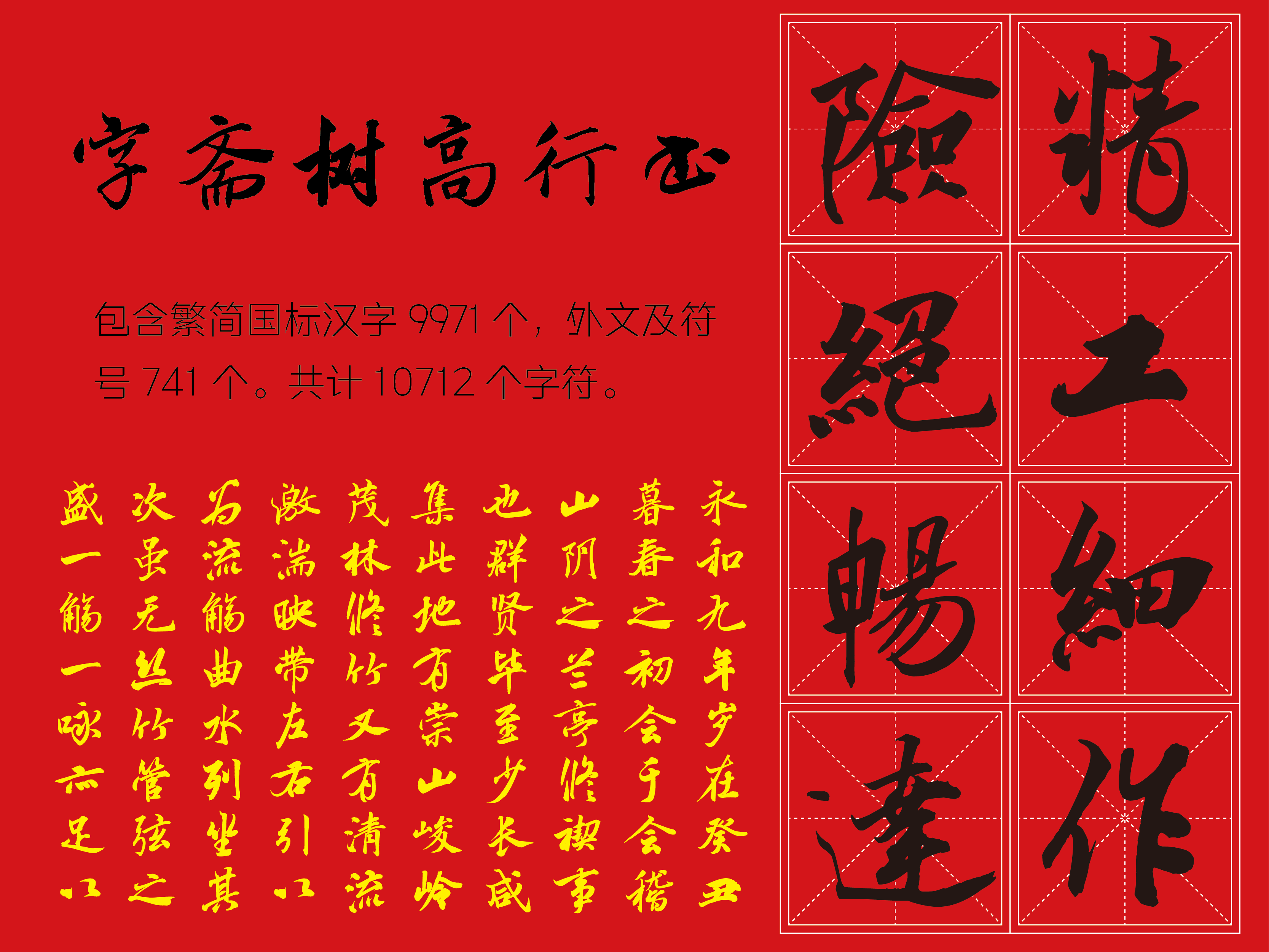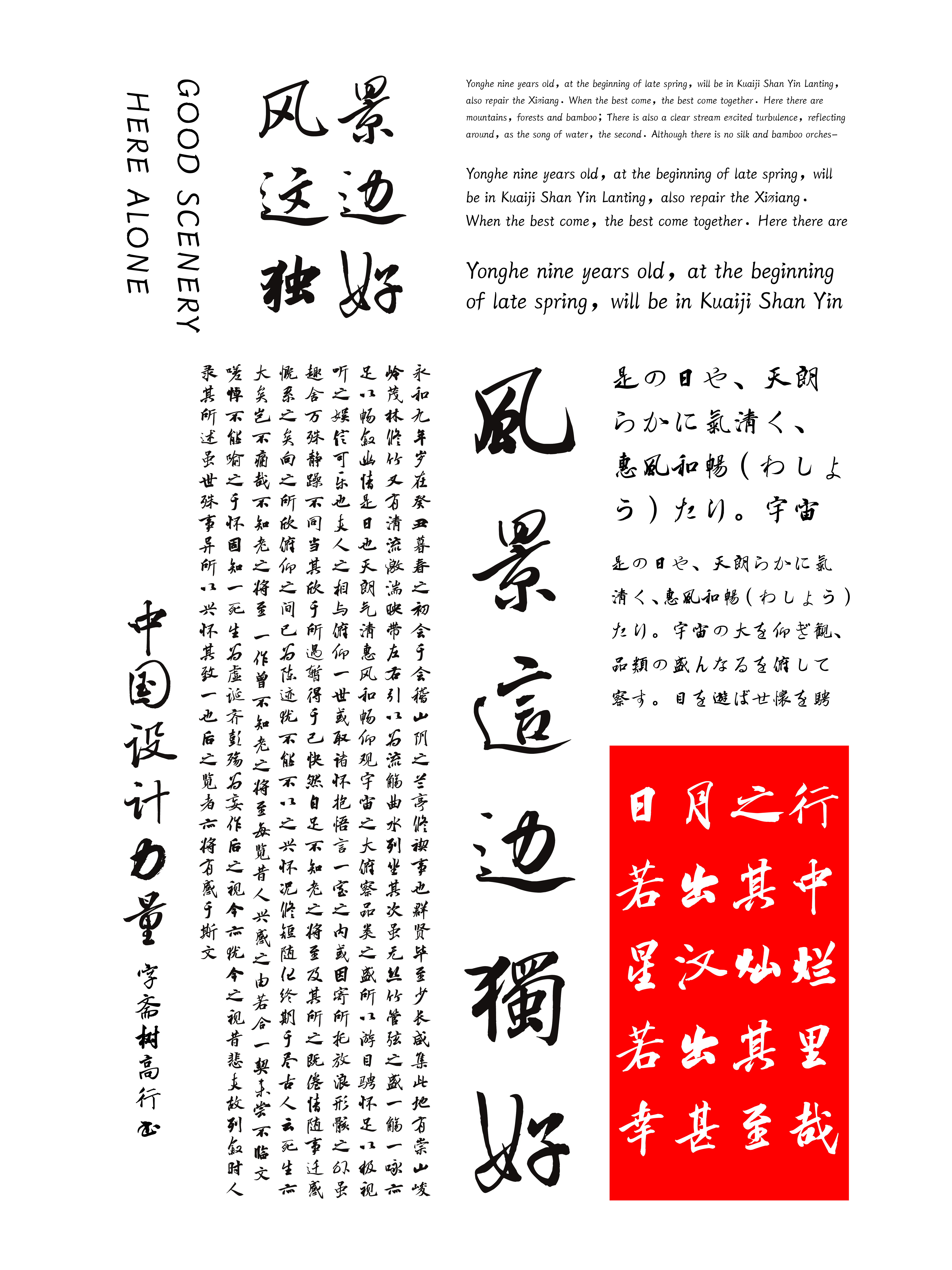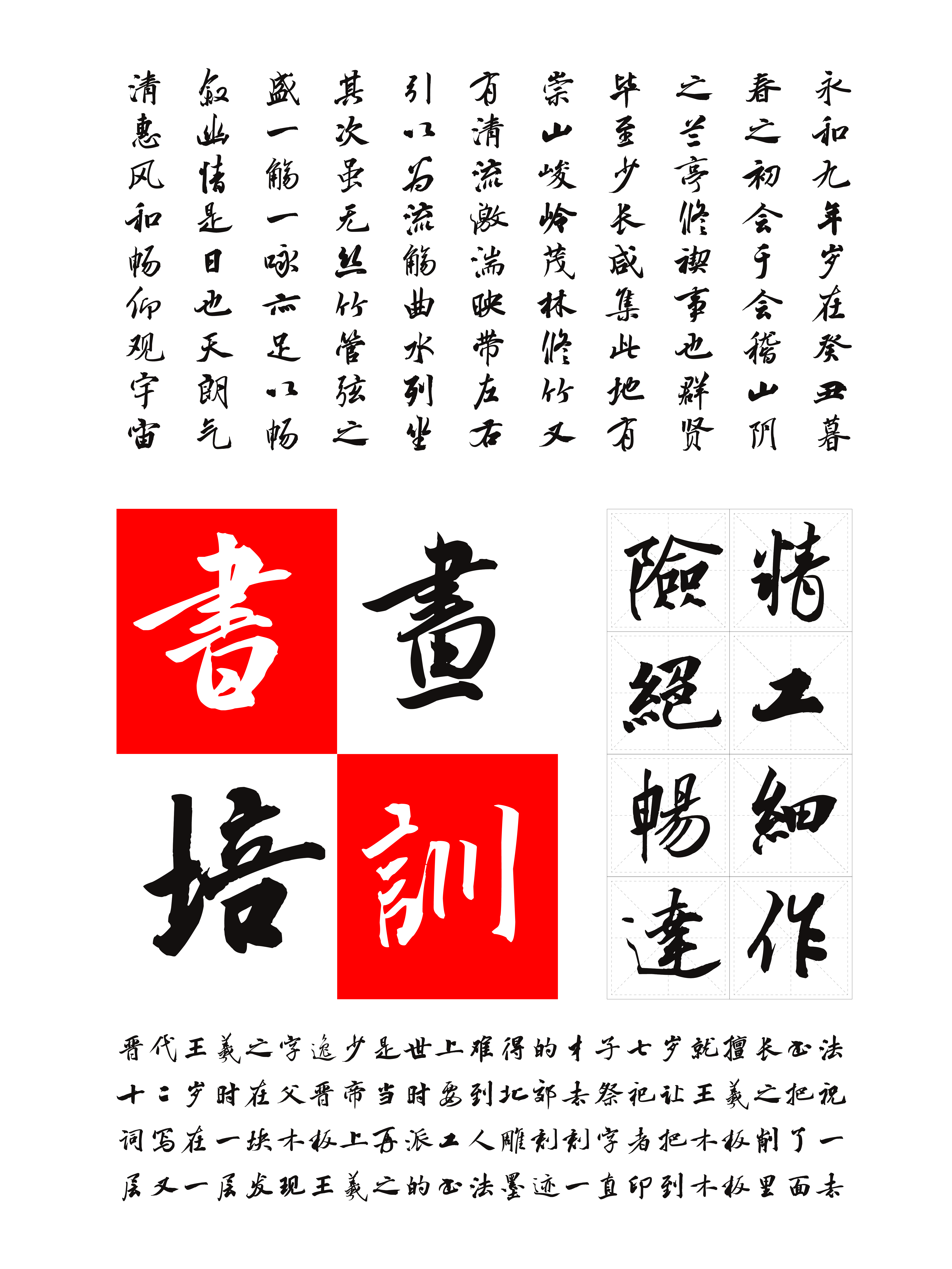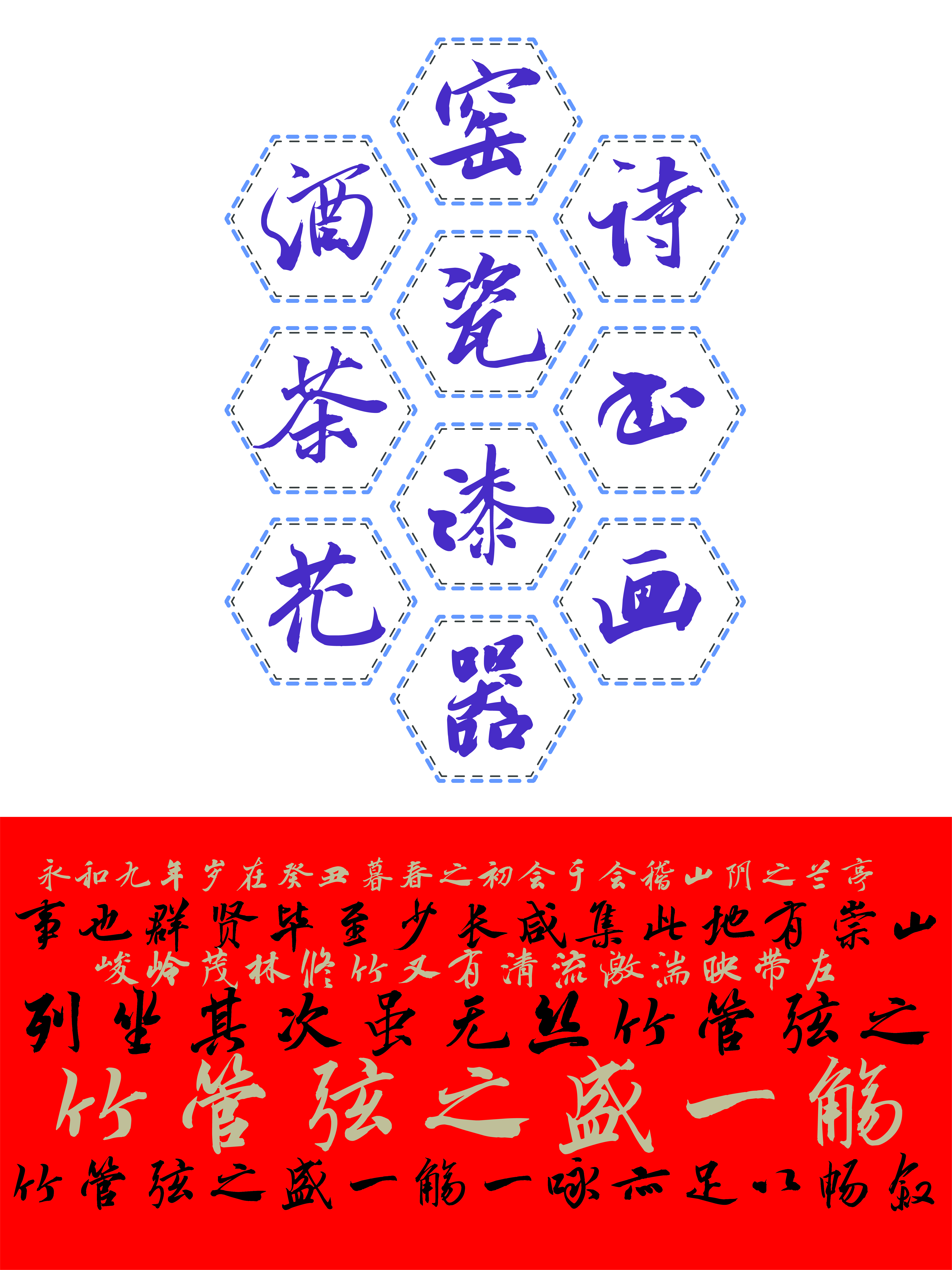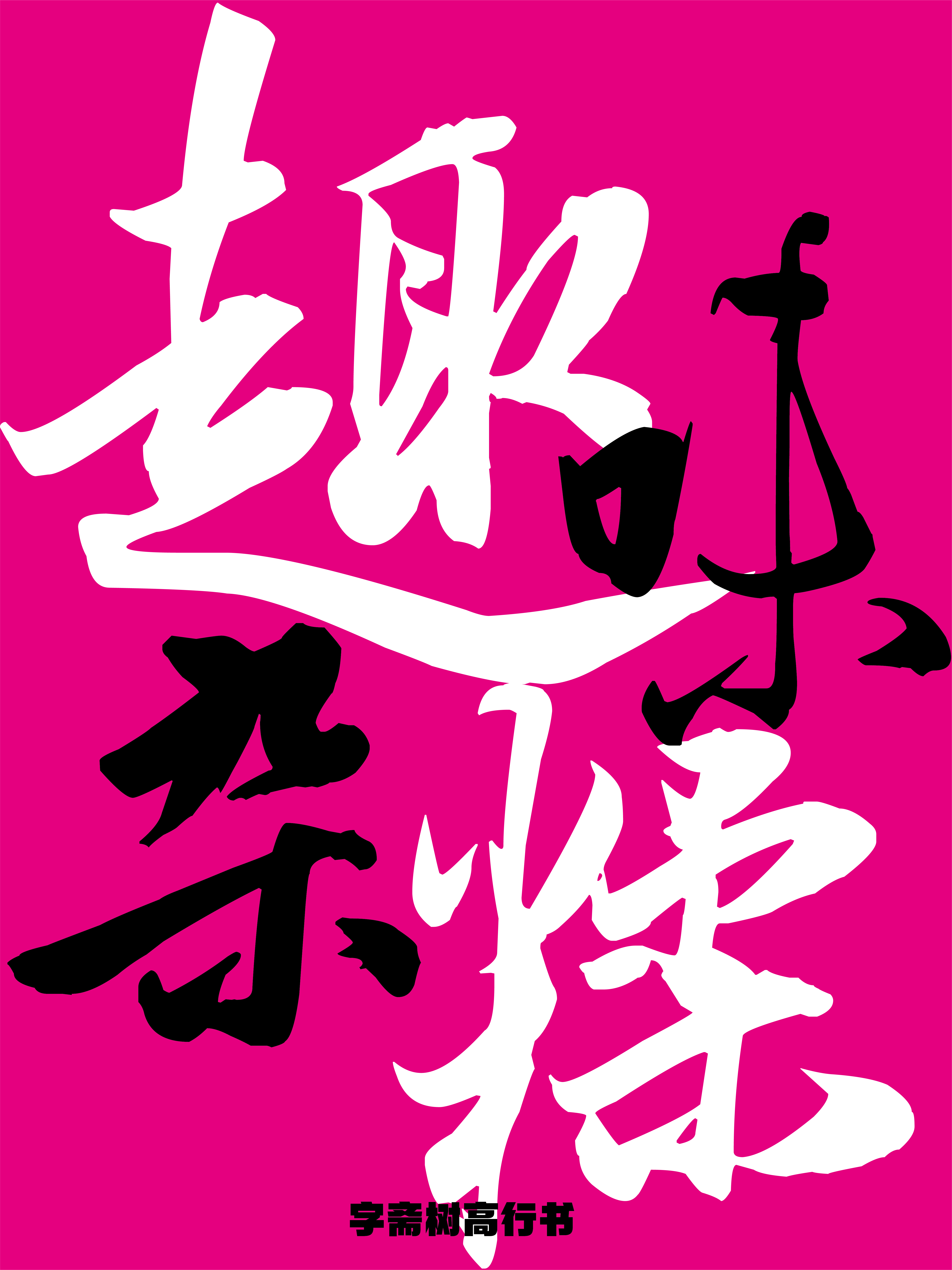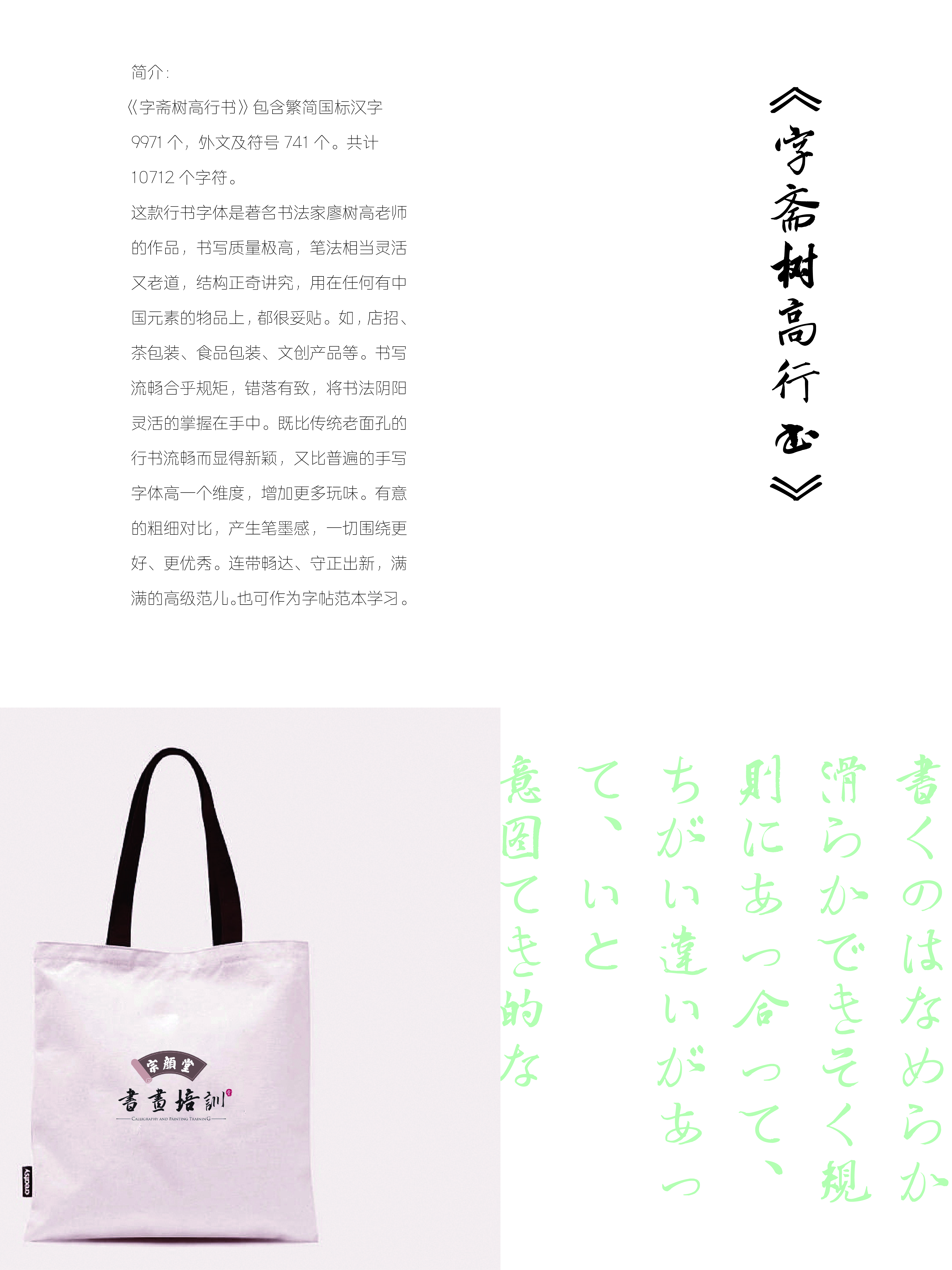
字斋树高行书
字斋树高行书,这款行书字体是著名书法家廖树高老师的作品,书写质量极高,笔法相当灵活又老道,结构正奇讲究,用在任何有中国元素的物品上,都很妥贴。如,店招,茶包装,食品包装,文创产品等。书写流畅合乎规矩,错落有致,将书法阴阳灵活的掌握在手中。既比传统老面孔的行书流畅而显得新颖,又比普遍的手写字体高一个维度,增加更多玩味。
字斋树高行书字体介绍